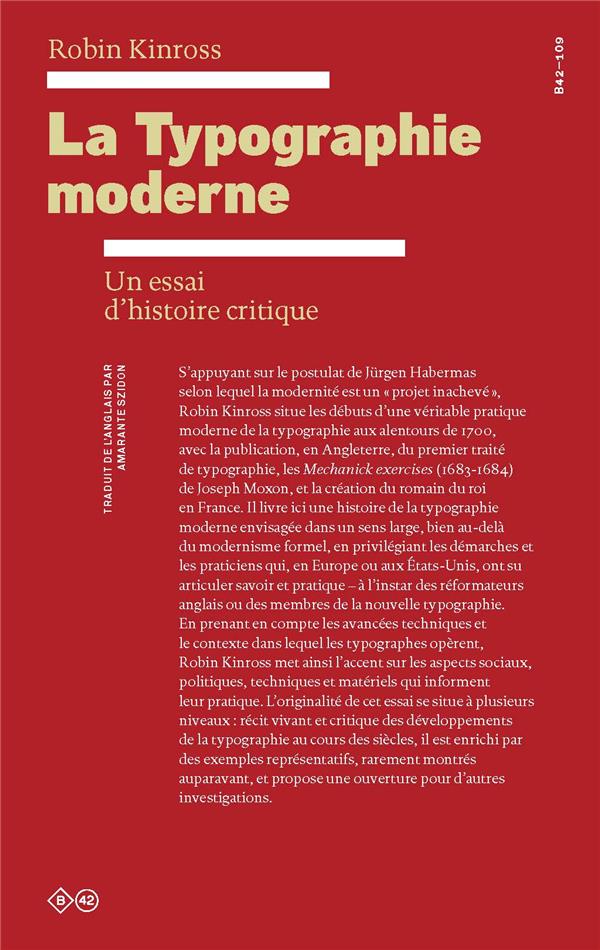
Livre neuf. La typographie moderne: un essai d'histoire critique. Dans ce dense essai, le typographe et éditeur Robin Kinross s'intéresse à l'établissement, à partir du XVIIe siècle d'une typographie qu'il qualifie de moderne, suivant la fameuse citation de Habermas associant la modernité à un "projet inachevé". De la France de Louix XIV aux cas spécifiques de l'Allemagne, des Pays-Bas et Belgique ou de la Suisse, jusqu'aux Etats-Unis, il entreprend et analyse une histoire critique des débuts de la typographie en tant que discipline, enrichie de considérations sociales, politiques, techniques et technologiques.
Contient en fin d'ouvrage des exemples reproduits dans des éditions anciennes de livres fameux, et une postface relative aux illustrations.